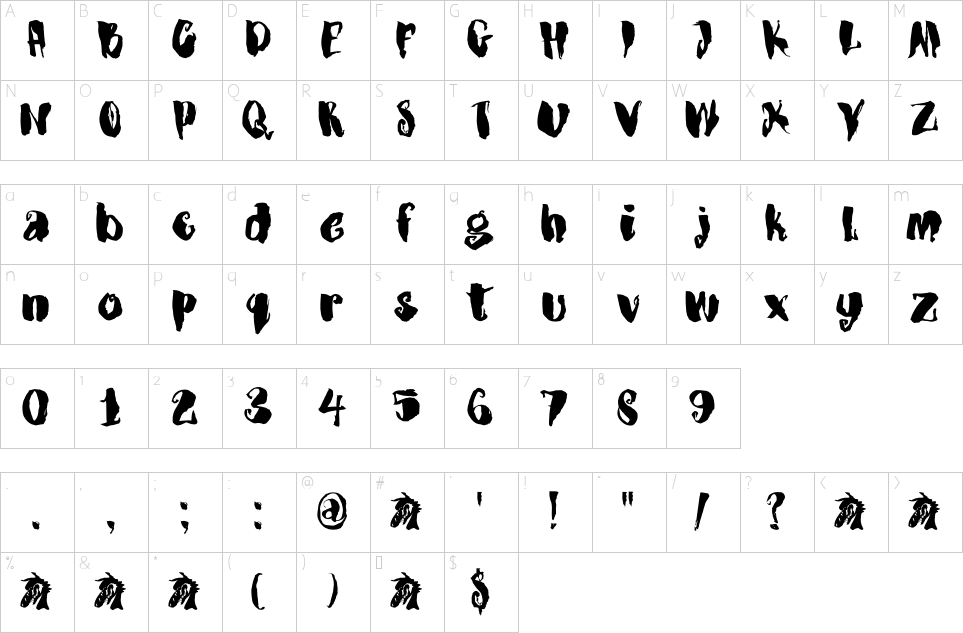
DK Dragonblood é uma fonte elegante e única que se destaca entre as muitas opções disponíveis na Internet. Desenvolvida por Hanoded, esta fonte recebeu uma grande recepção pelos seus detalhes artísticos e aprimoramentos da escrita feitos para oferecer um visual único e impecável. Com seu design elaborado e personalizado, DK Dragonblood pode ser a escolha perfeita para aqueles que buscam uma fonte diferenciada para destacar seu trabalho gráfico ou tipográfico. O fato de ter sido baixada mais de 12.430 vezes pela comunidade digital testemunha o reconhecimento e os elogios recebidos por esta font exclusiva. Em resumo, DK Dragonblood é uma ótima opção para quem busca agregar estilo e originalidade a seus projetos com um toque de fantasia no design da tipografia.